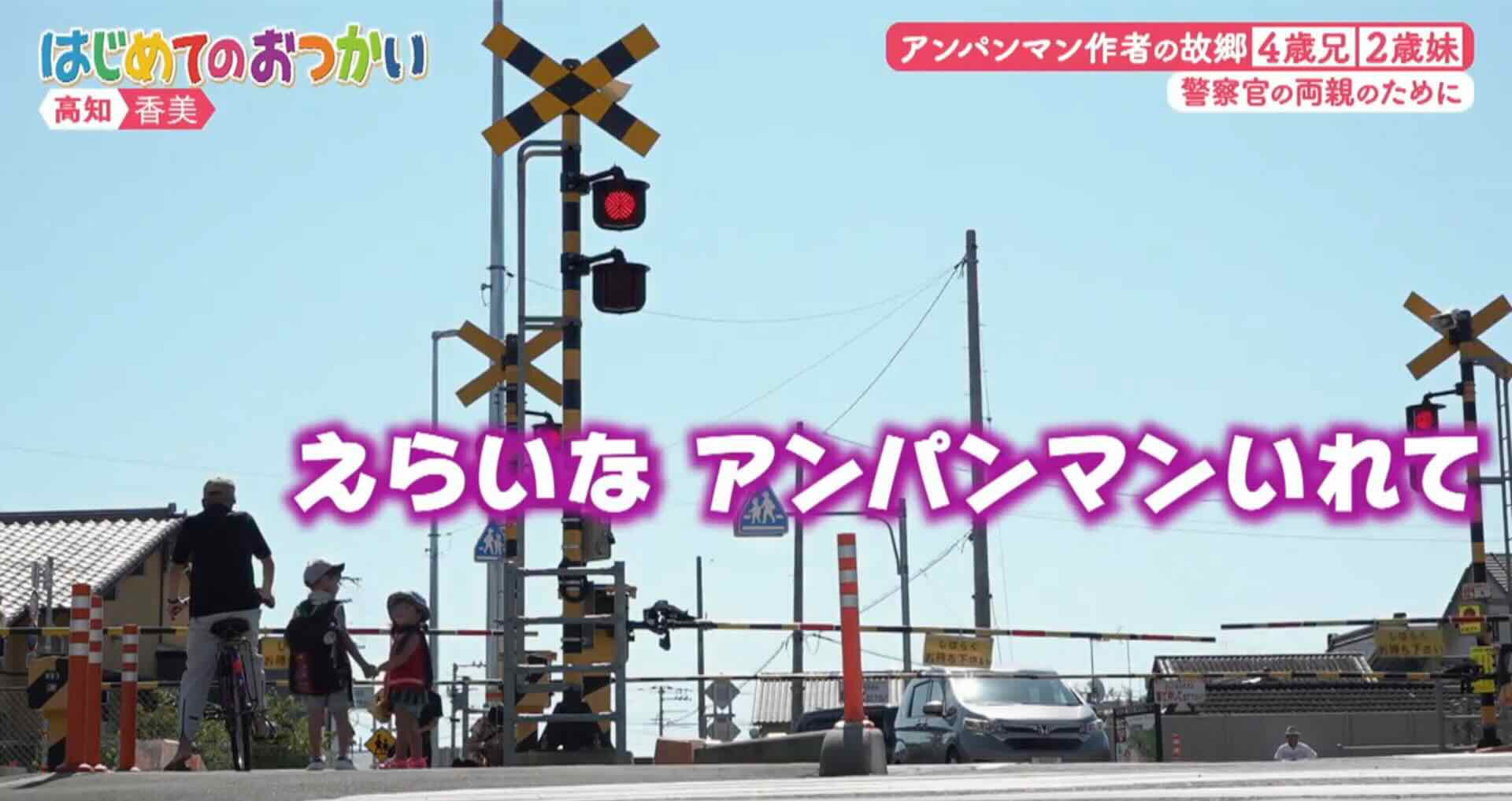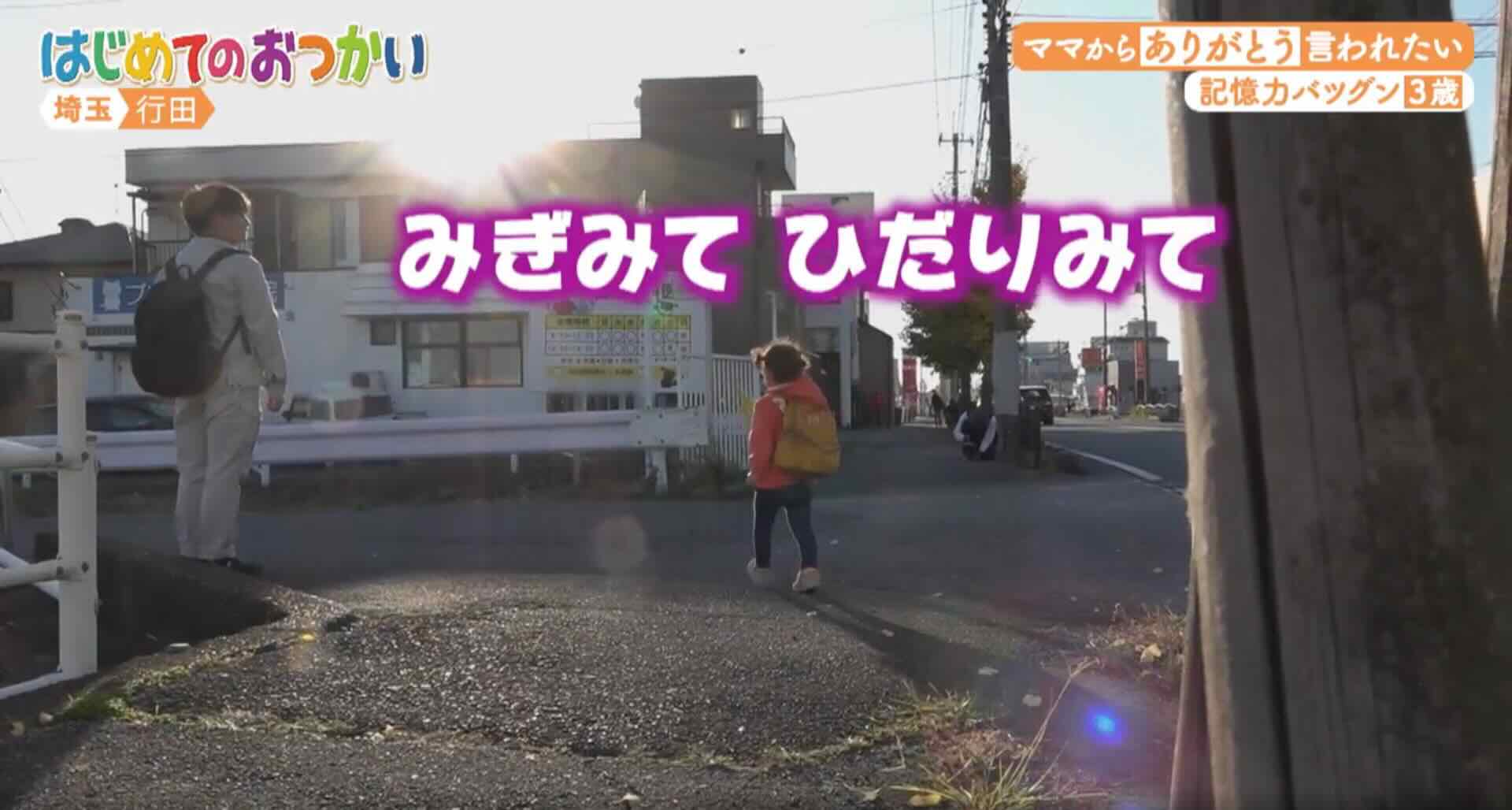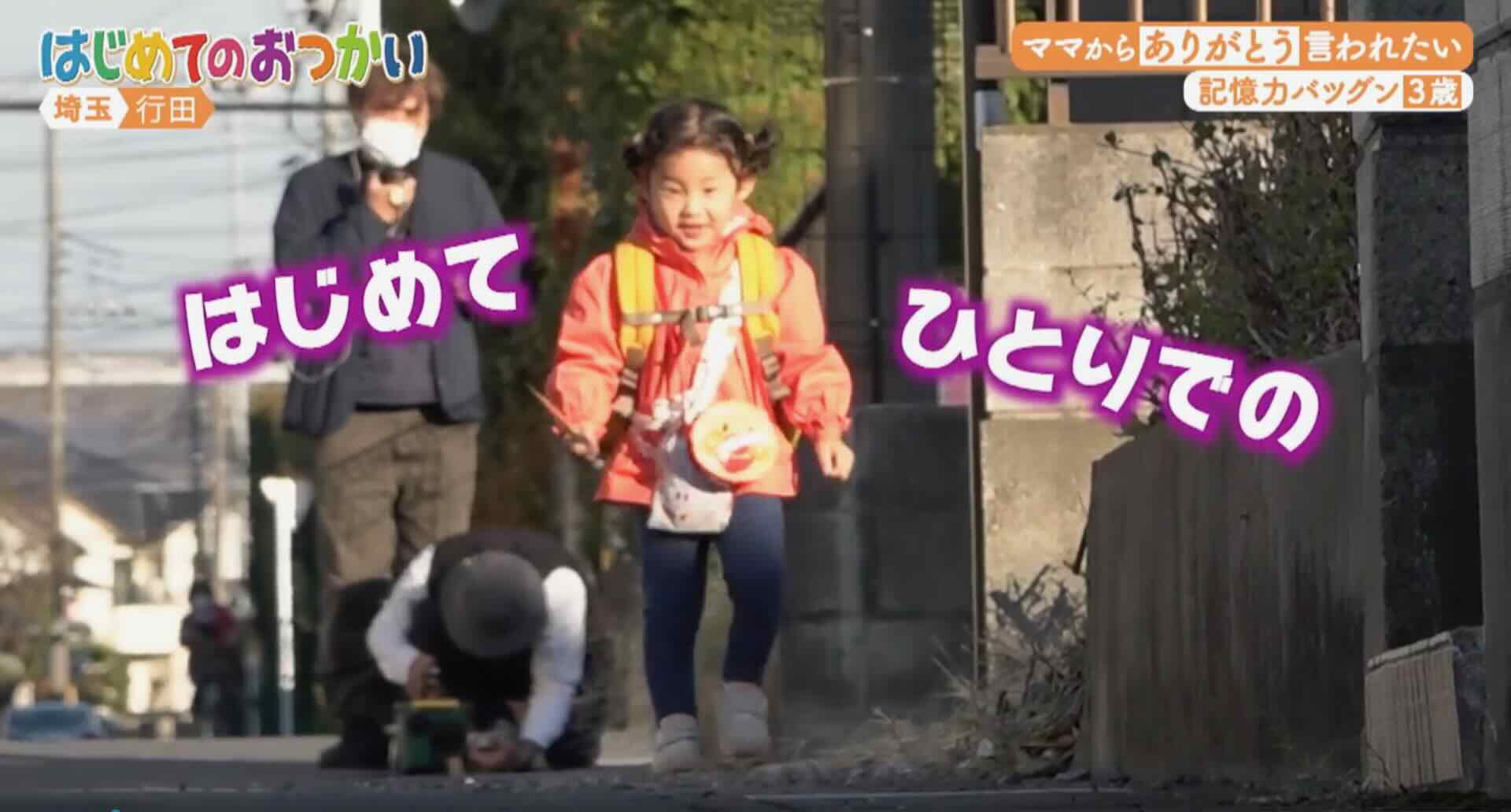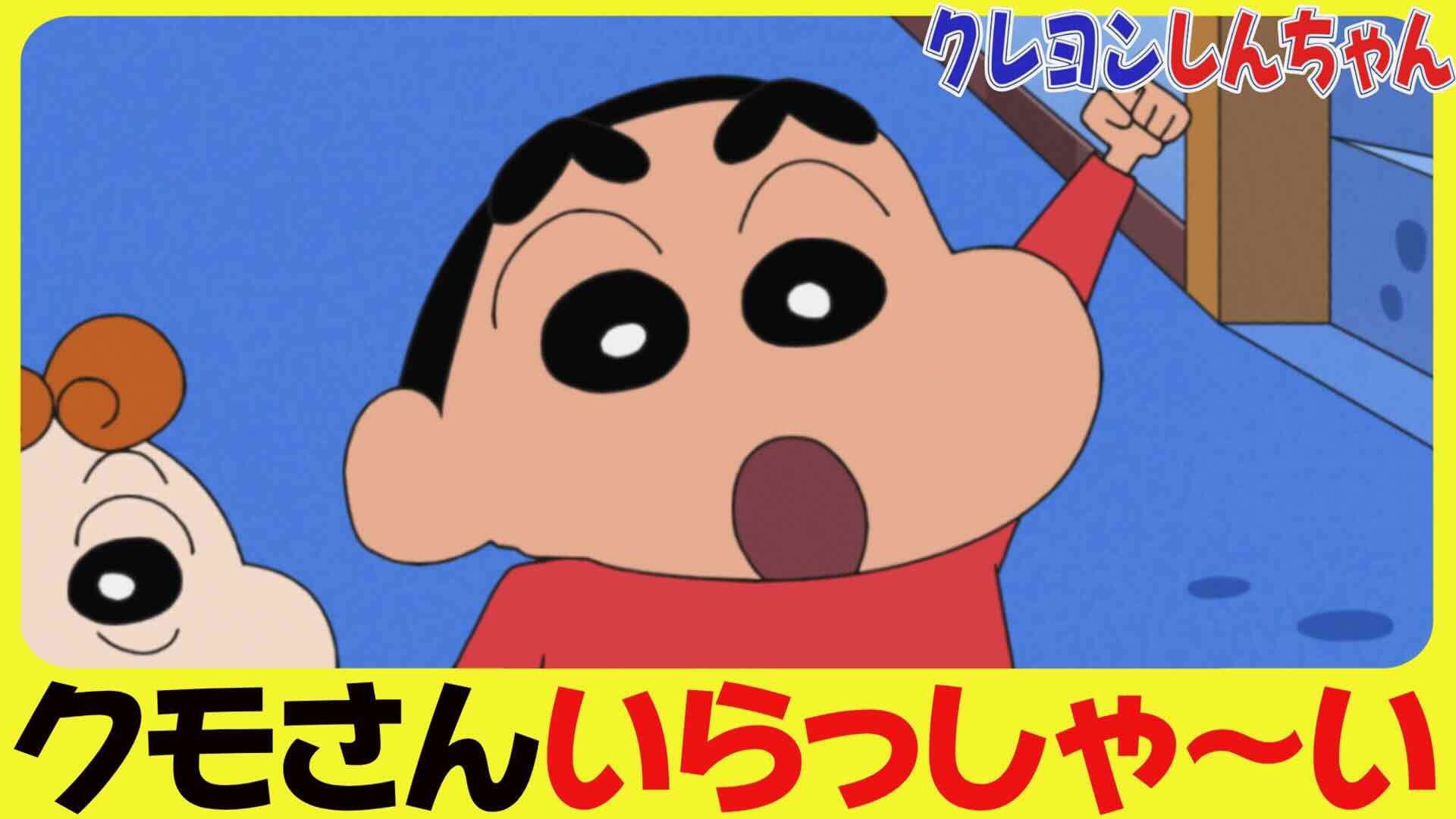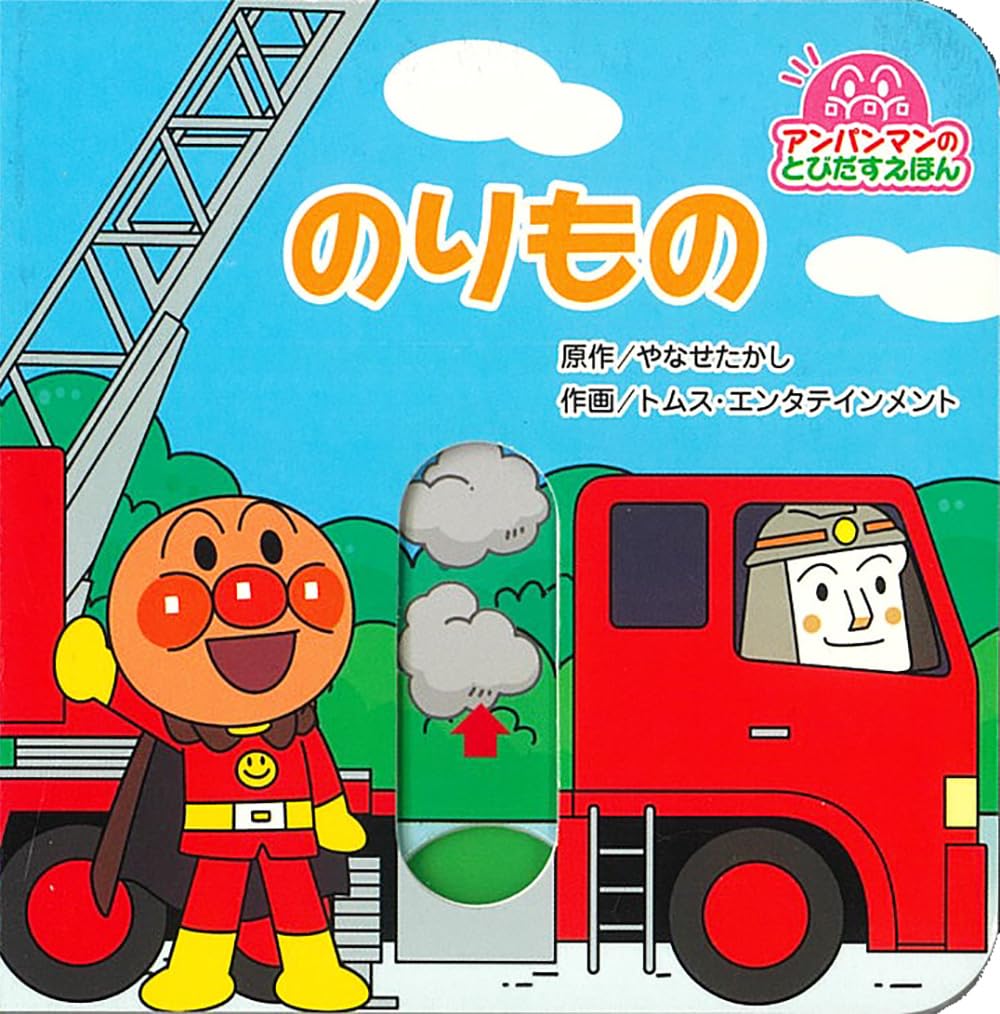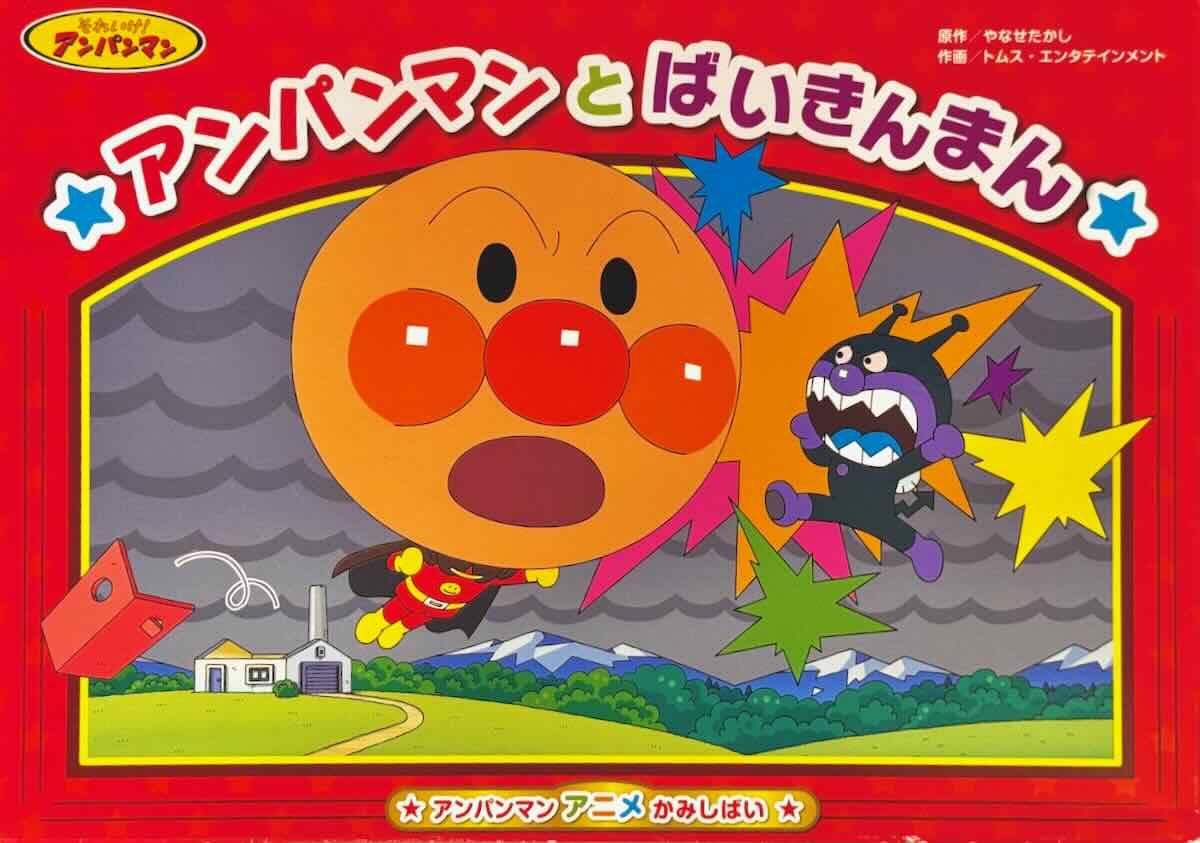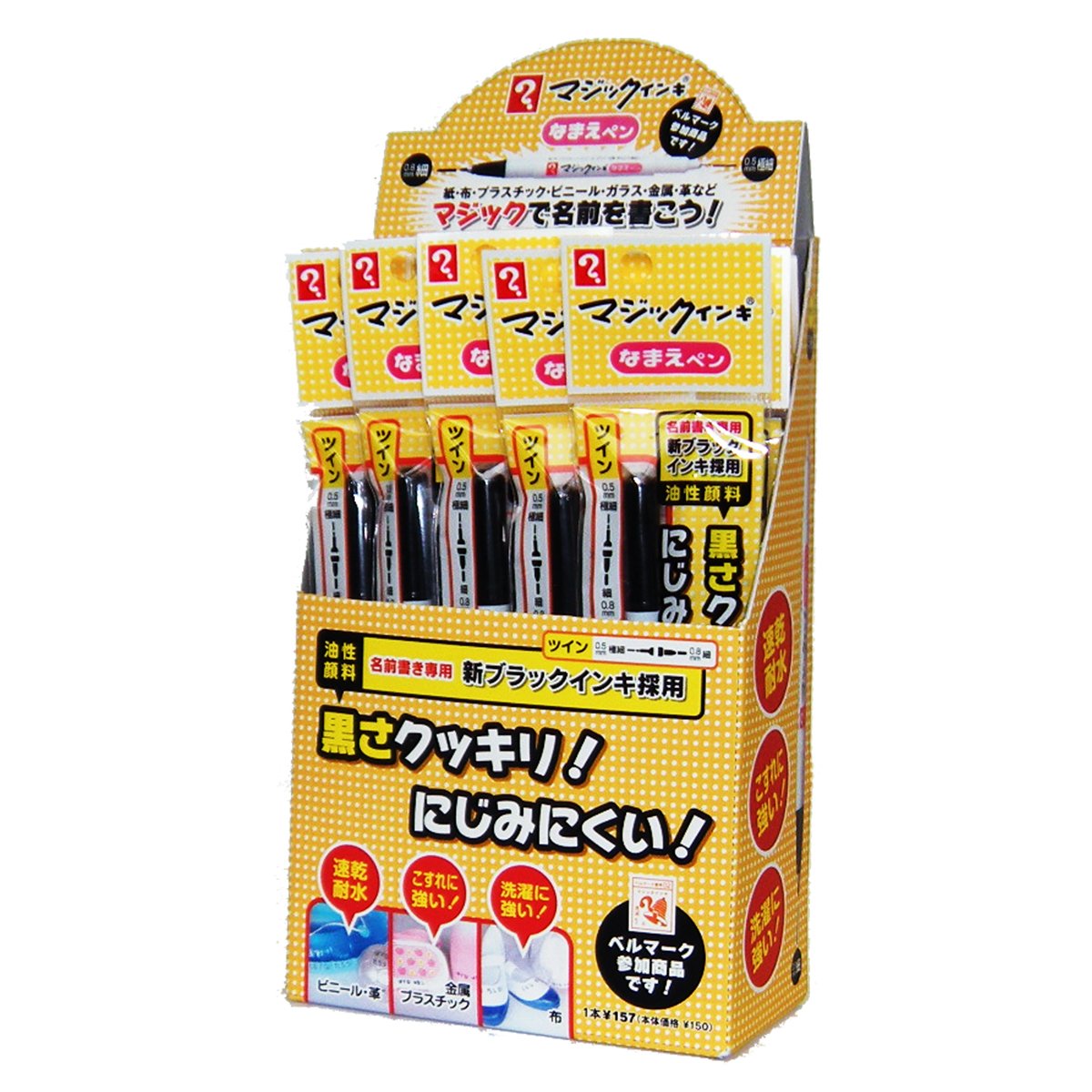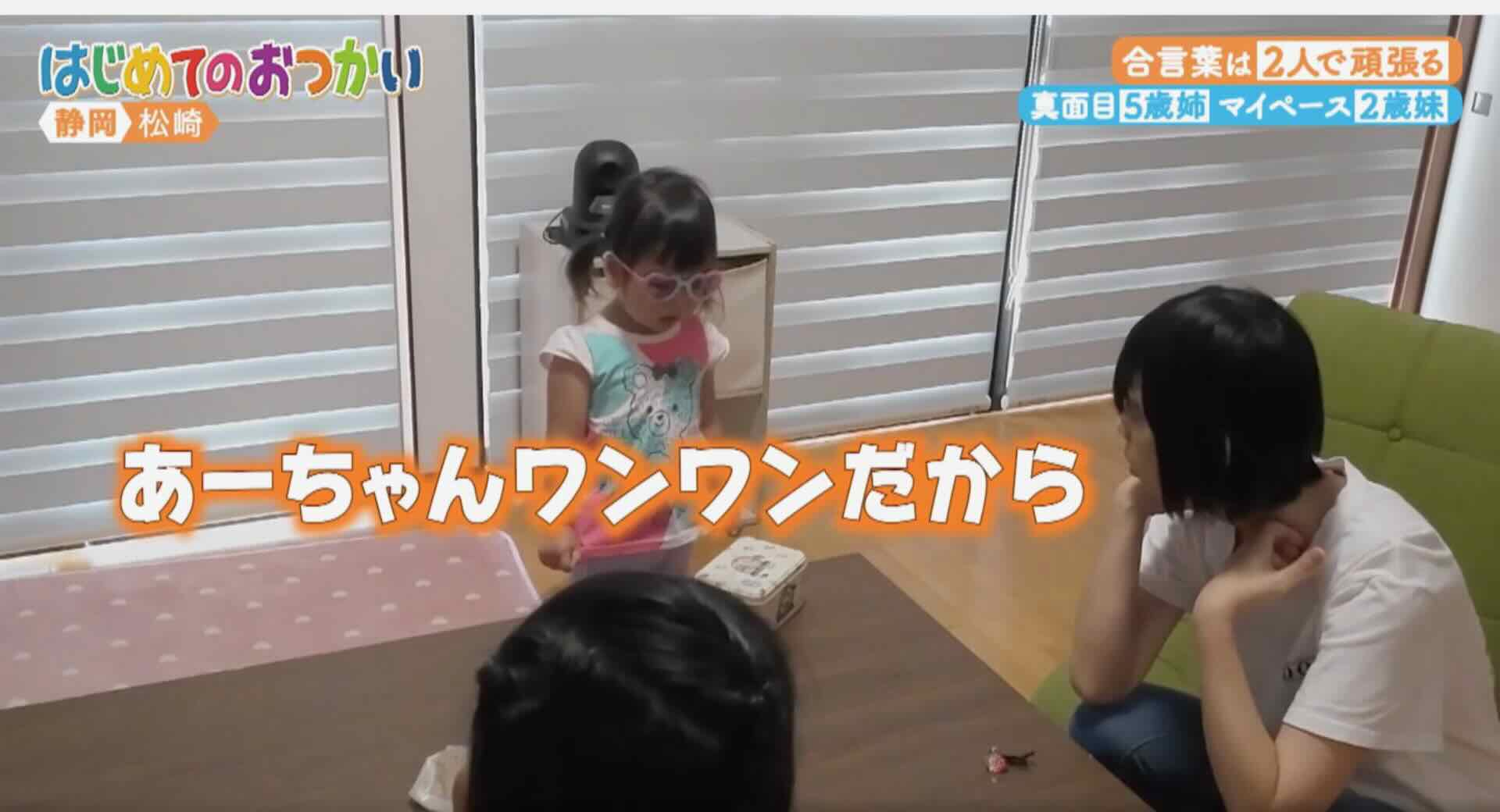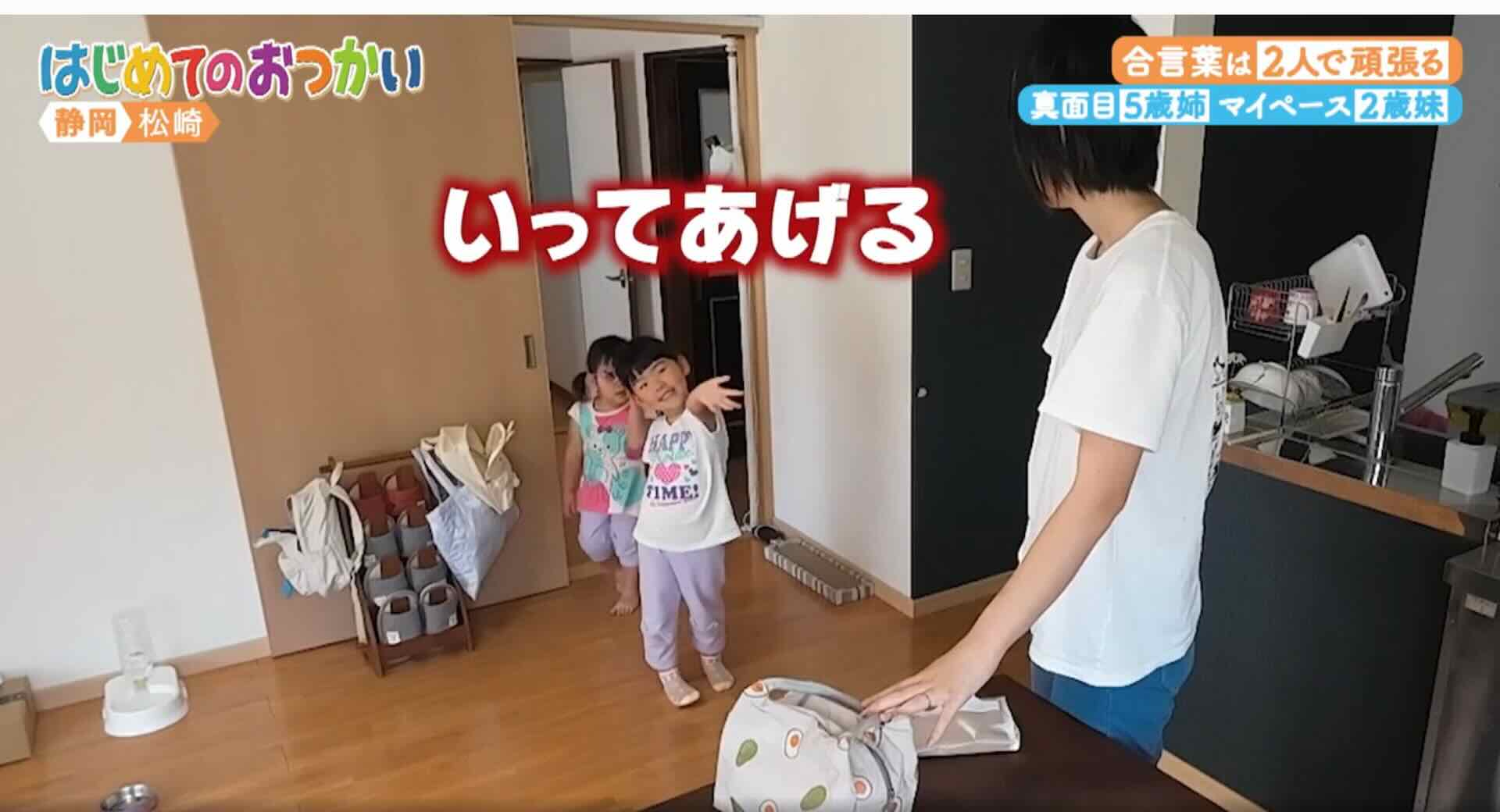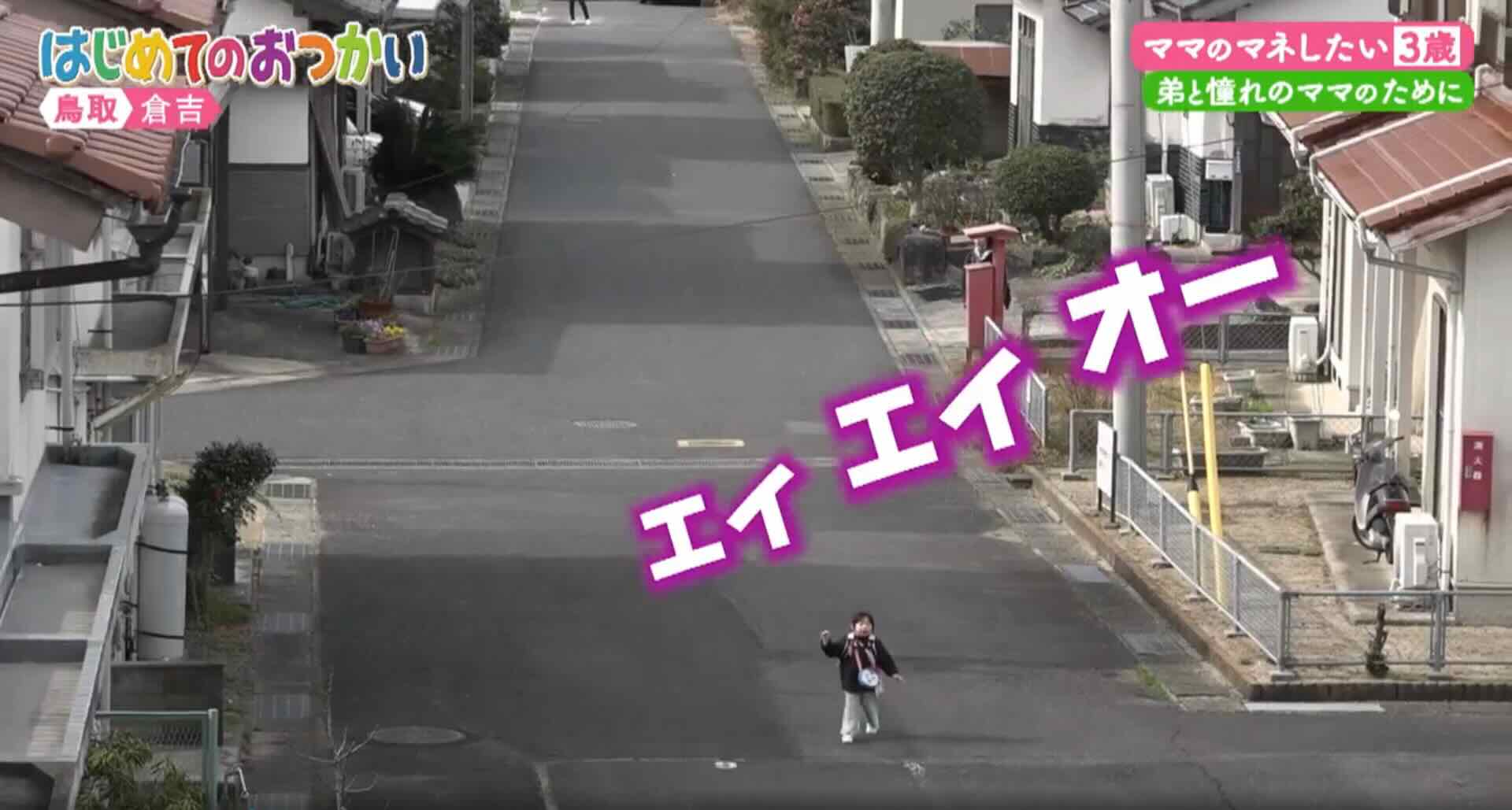
フォントワークスやモリサワから販売され親しまれている、かな書体「ハッピー」
日本テレビ系列の「はじめてのおつかい」。
これも。
まだある。
子供のセリフは、すべてハッピー書体のようだ。
もうひとつ。
誰でも知っている有名な筆記具。
全体像。
これも。
人気アニメのサムネール画像。
これも。
まだある。
もうひとつ。
日本テレビ「はじめてのおつかい」。
これも。
まだある。
まだある…。
書名:アンパンマンとばいきんまん
書名:こんにちは!
書名:のりもの
書名:どうぶつ
書名:わくわくびっくり!
書名:ポコポコ かくれんぼ